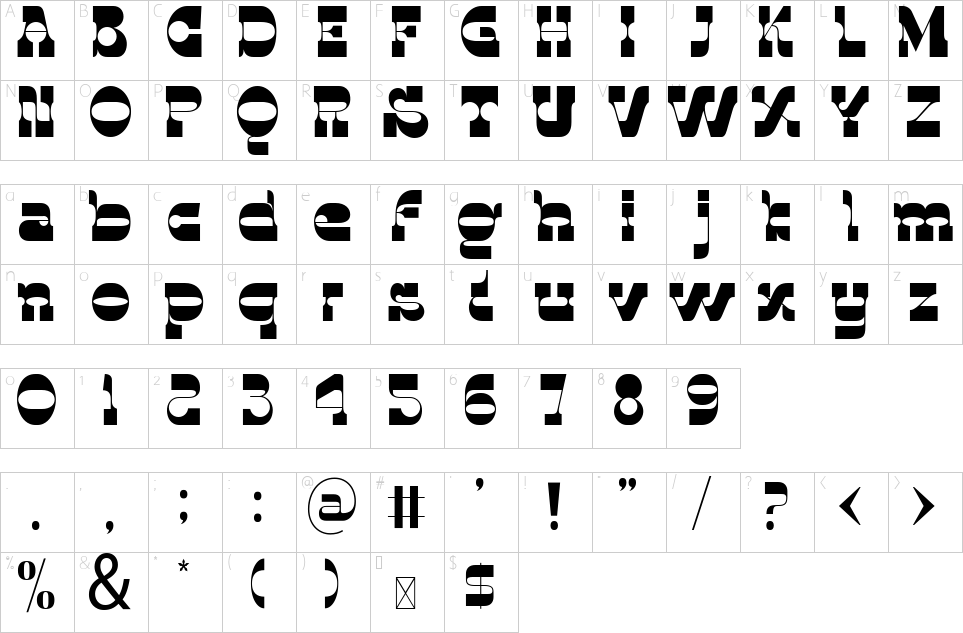
A Justice Ratkati é uma fonte gratuita que trouxe um novo nível de elegância e originalidade para o design digital. Desenvolvida pelo estúdio 177Studio.com, esta fonte é perfeita para designers que valorizam criatividade e qualidade. Com uma arquitetura de letras equilibrada e uma tipografia fluida, a Justice Ratkati traz uma aparência moderna e atraente que se destaca em qualquer projeto. Sua versatilidade é inigualável, permitindo que designers de diversos níveis experimentem suas múltiplas variantes, incluindo negrito e itálico, e até mesmo um efeito de negrito alternativo para um efeito de profundidade. O fato de ser uma fonte gratuita não diminui sua qualidade; ao contrário, ela oferece um excelente valor para designers que buscam recursos de design de alta qualidade sem precisar gastar muito. Esta fonte é um excelente complemento para qualquer projeto gráfico.